Как выбрать подходящий шрифт для инфографики на Вайлдберриз: полезные советы
Узнайте, как выбрать и использовать самый подходящий шрифт для создания привлекательной и информативной инфографики на сайте Вайлдберриз. Мы подсказываем, какие шрифты и комбинации использовать, чтобы ваша инфографика выглядела стильно и читабельно.
Выбирайте чистые и легко читаемые шрифты для основного текста инфографики.
Используйте разные размеры шрифтов, чтобы выделить заголовки и подзаголовки.
При создании инфографики для Вайлдберриз учитывайте особенности бренда и его целевую аудиторию.
Используйте жирные или курсивные варианты шрифта, чтобы выделить ключевую информацию в инфографике.
Не используйте слишком маленький шрифт, чтобы информация оставалась читабельной.
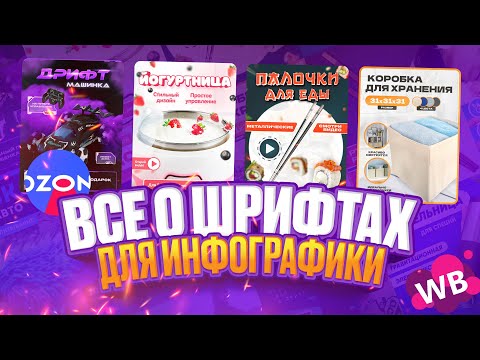
Помните о цветовой гамме: шрифты в инфографике должны хорошо сочетаться с фоном и другими элементами дизайна.
Экспериментируйте с разными шрифтами и их комбинациями, чтобы найти уникальный стиль для своей инфографики.
Не бойтесь использовать нестандартные шрифты, но убедитесь, что они читабельны и хорошо смотрятся на экране.
Проверяйте читабельность шрифтов на разных устройствах, включая мобильные телефоны и планшеты.
Не забывайте о правильном оформлении текста: выравнивание, интерлиньяж и межбуквенное расстояние влияют на восприятие инфографики.